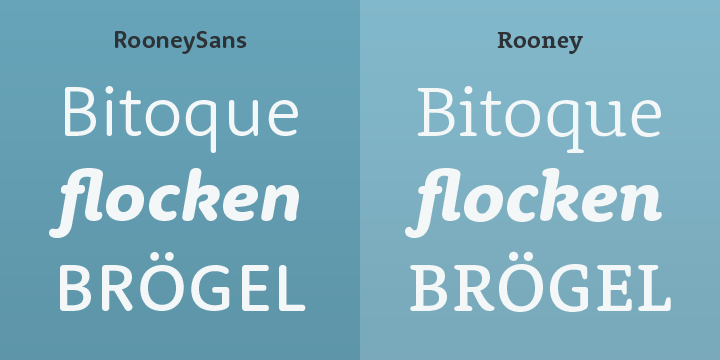
Die Rooney hat Zuwachs bekommen … Momentan kostet sie sogar nur die Hälfte!
Mit diesem ẞ würde ich nicht mal ein Viertel zahlen …
Das sieht grauslich aus.
Ja, mit der Form bin ich auch nicht so glücklich. Andererseits ist es wenigstens konsequent – wenn man die Basis dazu betrachtet:
Da funktionierte es für mein Empfinden schon besser.
Was bringt die Konsequenz, wenn das Ergebnis missfällt? :-?
Ja. Es fällt eben jetzt ohne Serifen optisch größer bzw. weiter aus und deswegen wirkt es so »gakelig«. Vielleicht hätte ein minimales Ausgleichen geholfen ohne gleich die ganze Form über den Jordan zu werfen?
Was gefällt euch denn nicht?
Oben links ist es durch die Ecke ja etwas kantig, aber da reißen m. E. die meisten anderen (runden) Formen eine Lücke. Das missfällt mir meistens.
Außerdem finde ich, dass sich der Buchstabe insgesamt gut einfügt (mal davon abgesehen, dass er sich noch nicht so in der Sehgewohnheit etabliert hat, wie der Rest der Zeile).
Was gefällt euch denn nicht?…
Die Form ist erstens in sich unausgewogen (zu eckig trifft zu rund) und zweitens im Vergleich zu den restlichen Buchstaben zu breit.
im Vergleich zu den restlichen Buchstaben zu breit.
Da es ja seine Historie in einer Ligatur hat (wie auch das W), was sich auch in der noch vorhandenen "Offenheit" zwischen den beiden Teilen zeigt, wäre das m.E. nicht sooo schlimm ...
Apropos Ligatur: Da dem Font das ſ fehlt (und auch das Ʒ), hat das [sZ][/sZ] ja eigentlich keine "Basis" in dem Font ...
Da es ja seine Historie in einer Ligatur hat …
Das interessiert aber den Leser nicht, weil er in einer Schrift zum Glück diese Historie nicht vor Augen hat. Du fährst doch heute auch nicht mehr mit einem blattgefederten Pkw und Holzvergaser, nur weil die Historie …
Was mich beim Versal-ß der Rooney stört, ist dass die Innenräume nicht wie bei den anderen Versalien wie A, B, E, F, H, K, R, S, und X mehr oder weniger übereinander stehen, sondern eine stark nach links oben neigende Achse bilden. Somit bildet es eine Ausnahme und das ist denke ich mit ein Grund dafür, dass dieses Zeichen sich nicht so richtig einfügt.
Spräche das nicht generell für die „runde Form“ ([sZ][/sZ]), welche den oberen Innenraum wieder etwas nach rechts in die Mitte drückt? Außerdem verhindert sie ja Assoziationen wie „I3-Ligatur“. ;-)
Wie ist denn Dein Verhältnis zum Versal-Eszett überhaupt? Bei Typolution laß ich heraus, dass Du diesem Buchstaben noch sehr skeptisch gegenüberstehst. Habe ich Dich da richtig verstanden?
Genau. Ich denke, wir brauchen das Versal-Eszett nicht wirklich. Genauso wie ich als Niederländer auf ein als Ligatur gezeichnetes IJ verzichten kann. SS funktioniert nach meinem Verständnis genauso gut. Notfalls könnte man noch über S mit macron nachdenken, das Macron war ein gängiges Mittel um Verdopplungen abzukürzen bzw. zu vermeiden, wie hier beim m: http://www.flickr.com/photos/moshdesigner/2857668228/ Ich empfinde die Verdopplung vom S nicht als Problem, weder formal, noch sprachlich, auch die rechtschreiblogik womit das Versal-Eszett neuerdings begründet wird kann mich nicht überzeugen. Deswegen gibt es da für mich als Designer nichts zu lösen.
Genau. Ich denke, wir brauchen das Versal-Eszett nicht wirklich. Genauso wie ich als Niederländer auf ein als Ligatur gezeichnetes IJ verzichten kann.
Das verstehe ich nicht. Inwiefern hältst Du die beiden Fälle für vergleichbar?
Sowohl das als Ligatur gestaltete IJ und das Versal-ß (für mich eine Ligatur aus ein imaginäres lang-S und einem S) sind kontraproduktiv. Ligaturen sind gestalterische Lösungen für gestalterische Probleme, wenn es kein Problem gibt, braucht man auch keine Lösung. Nicht für alle fi muss ein Ligatur gestaltet werden und aus der Existenz einer fi-Ligatur die Notwendigkeit einer FI-Ligatur ableiten zu wollen wäre eine unsinnige Konsequenz.
Ligaturen sind gestalterische Lösungen für gestalterische Probleme …
Das ist die »umgangssprachliche« Verwendung des Begriffs Ligatur. Korrekt ist sie nicht.
w/W, œ/Œ, æ/Æ sind auch Ligaturen und zwar keine gestalterischen, sondern sprachlich-funktionale. Und genau in diese Kategorie gehört ß/ẞ ohne jeden Zweifel. Denn so regelt es die amtliche Rechtschreibung*.
Wer das Eszett in heutiger Verwendung bei fi und fl einordnet, begeht einen sachlichen Fehler und das ist auch keine Frage von Meinungen.
* Bislang nur für das ß
Das eigentliche Problem, das mit einem Versal-ß gelöst wird, ist ja die mögliche Auflösung von Eigennamen aus der Versal- in die Minuskelschreibweise. Eigennamen verwenden das ß heute eben nicht als Ligatur aus langs und s oder Doppelung des s, sondern als eindeutigen Buchstaben – unabhängig davon, wie dieser Buchstabe mal entstanden sein mag (wie andere ja auch sich aus Ligaturen entwickelt haben). Meißen heißt eben Meißen, nicht Meissen.
tja. die frage ist halt ob man
a) alle nationalen behörden eine einheitliche schreibweise eintrichtern kann.
b) oder es doch einfacher ist ein eszett für den versalsatz zu entwerfen
c) man kann natürlich auch versuchen den bürgern einfach eine lockerheit beibringen.
ist doch sch***segal ist ob man mueller oder müller oder muller heißt. sind doch nur namen.
ich glaube b) ist die einfachste lösung ;)
ähnlich ist das übrigens mit augenfarben. asiaten habe schwarze augen, das gibts aber in
deutschland nicht und meistens wird dann einfach braun eingetragen.